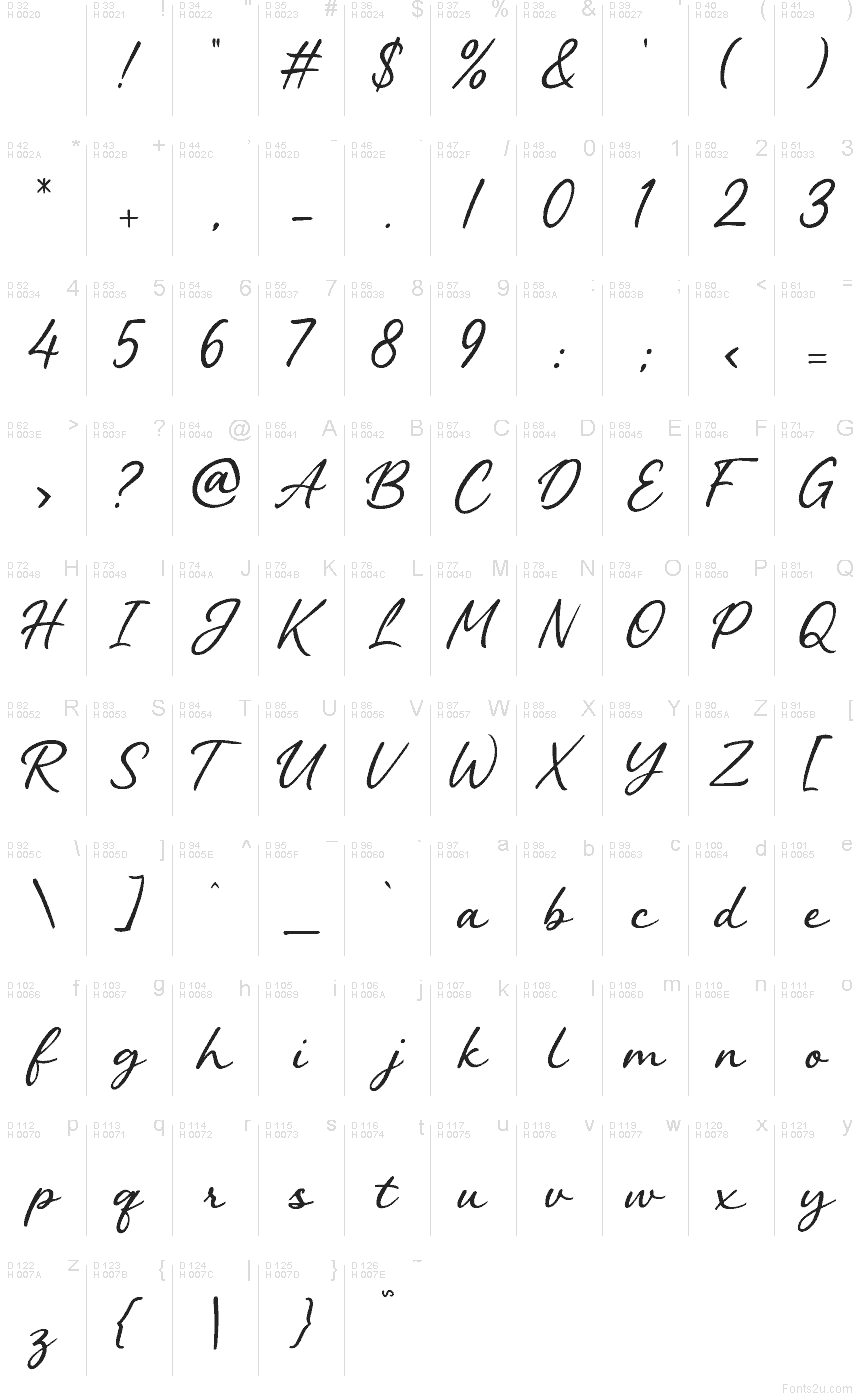
The Lady in the Boulevard, ručně psaný skript od BlackFridayFont, sází na módní eleganci s dlouhými, rozmáchlými tahy a uvolněným, osobním rytmem. Písmena působí vzdušně a lehce dramaticky, s vysokými náběhy, smyčkovými spoji a plynulostí jako u podpisu, díky čemuž si styl zachovává půvab a není příliš upjatý.
Hodí se pro branding, butikové obaly, knižní obálky, kavárenské menu a pozvánky, kde může bezplatné písmo dodat šmrnc bez zbytečné strnulosti. Použijte ho na krátké titulky, kartičky, citáty nebo monogramy, zejména tehdy, když ty prodloužené tahy mohou protnout layout a částečně ho samy ozdobit.